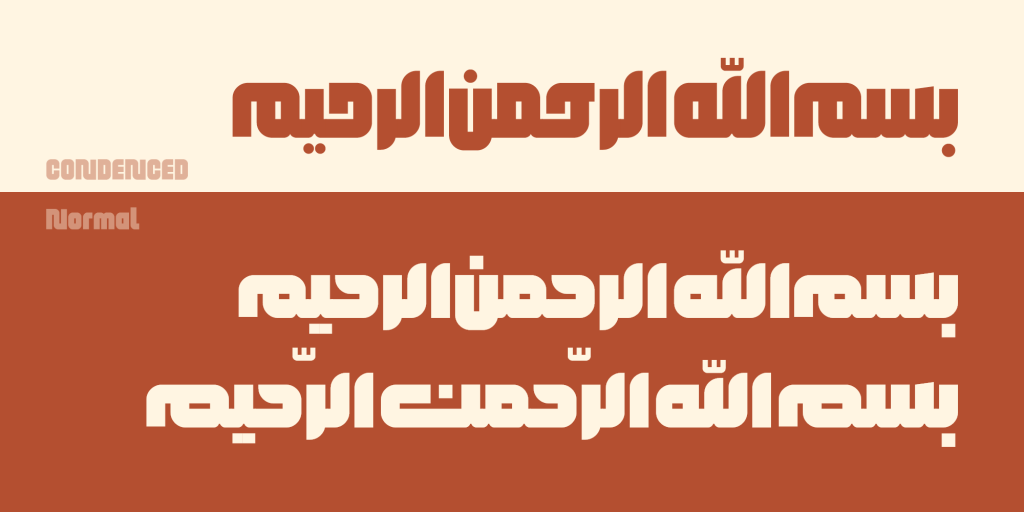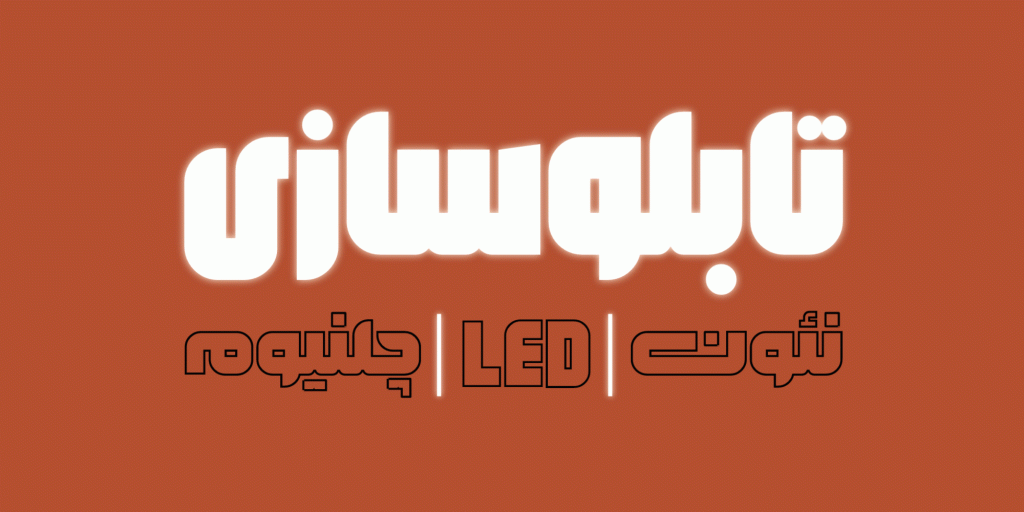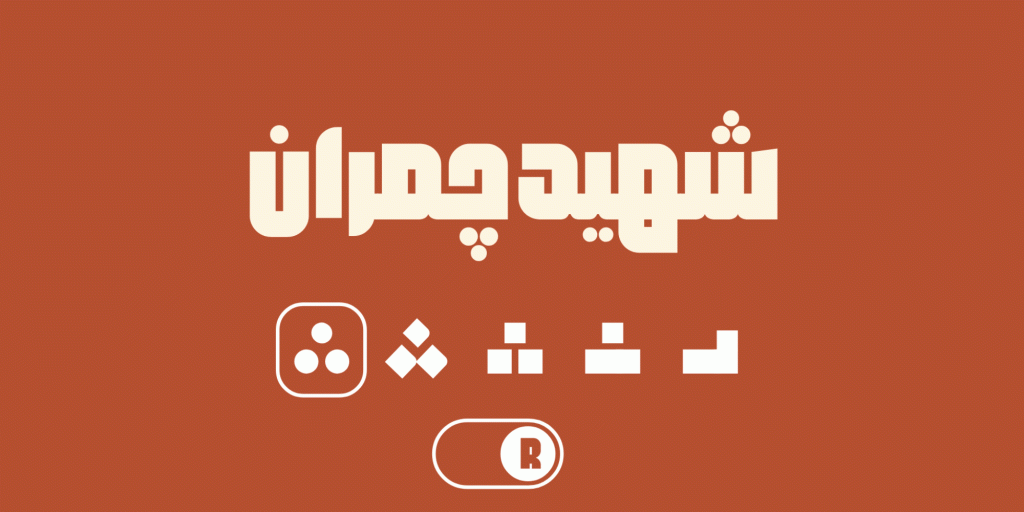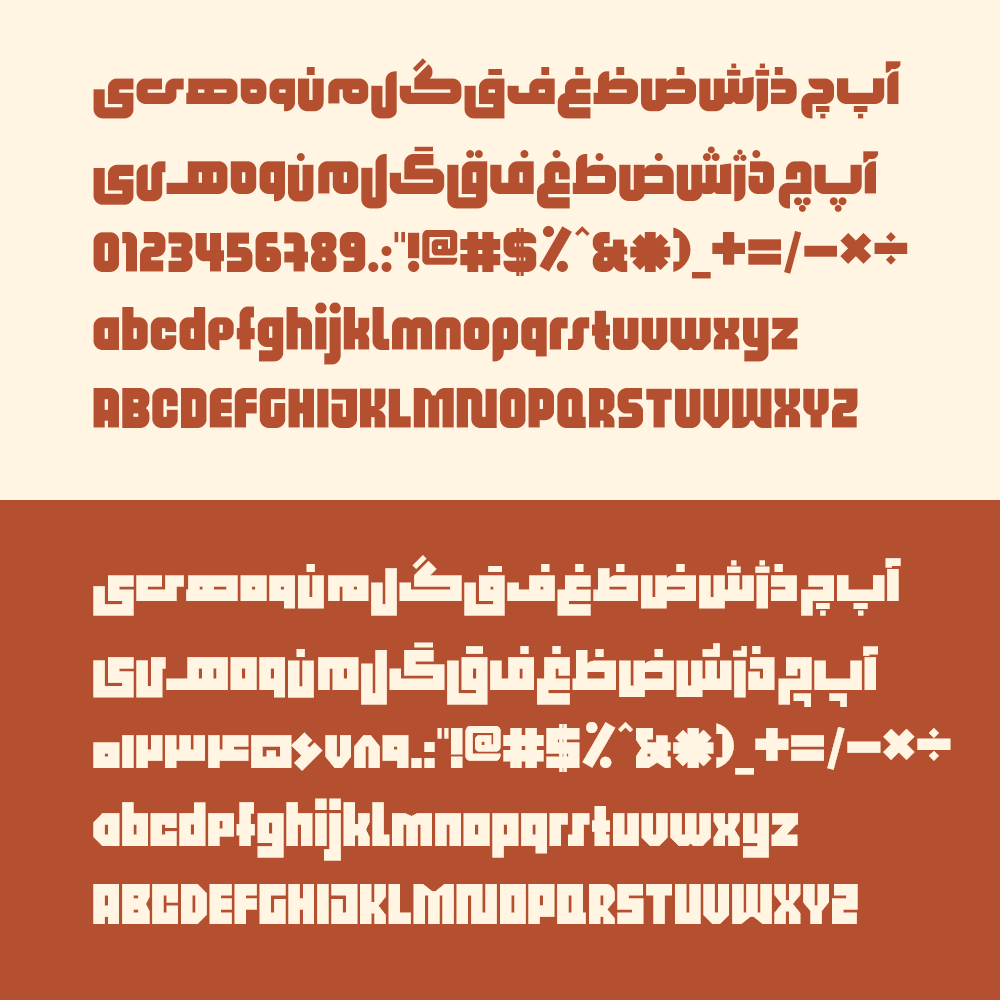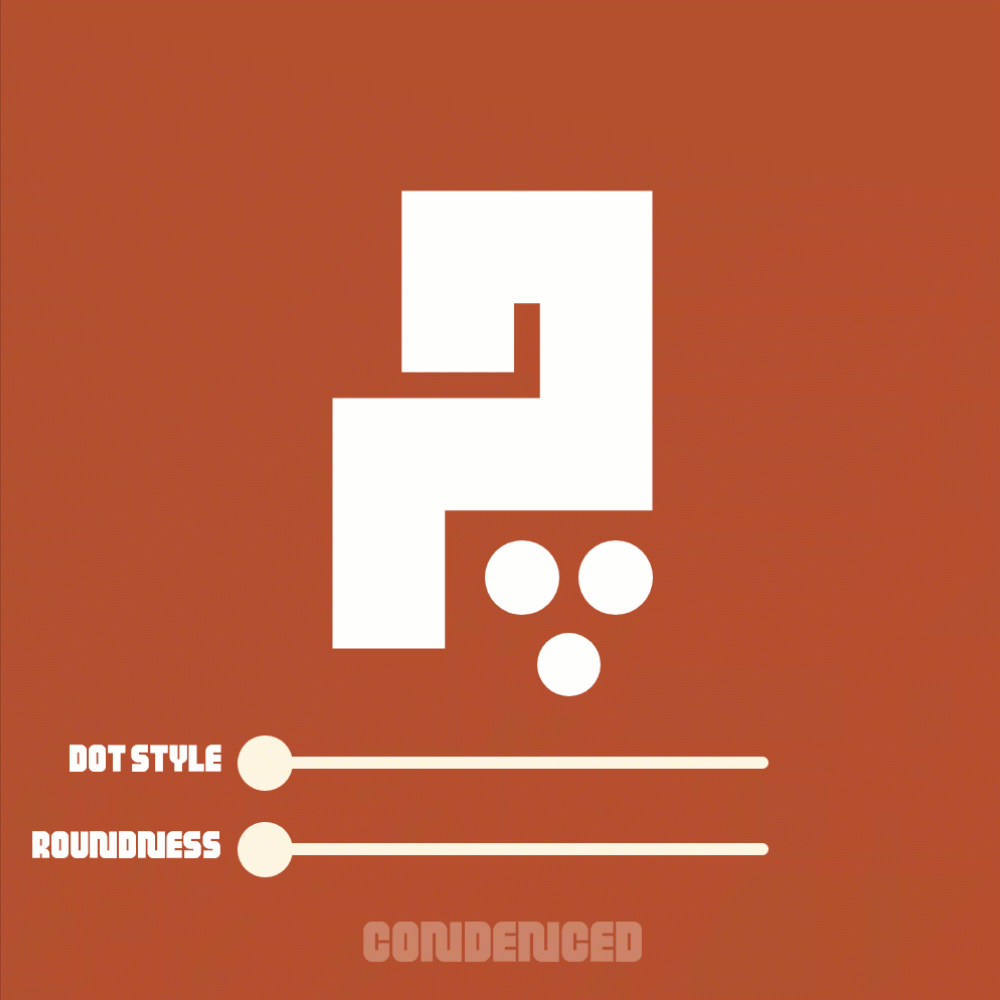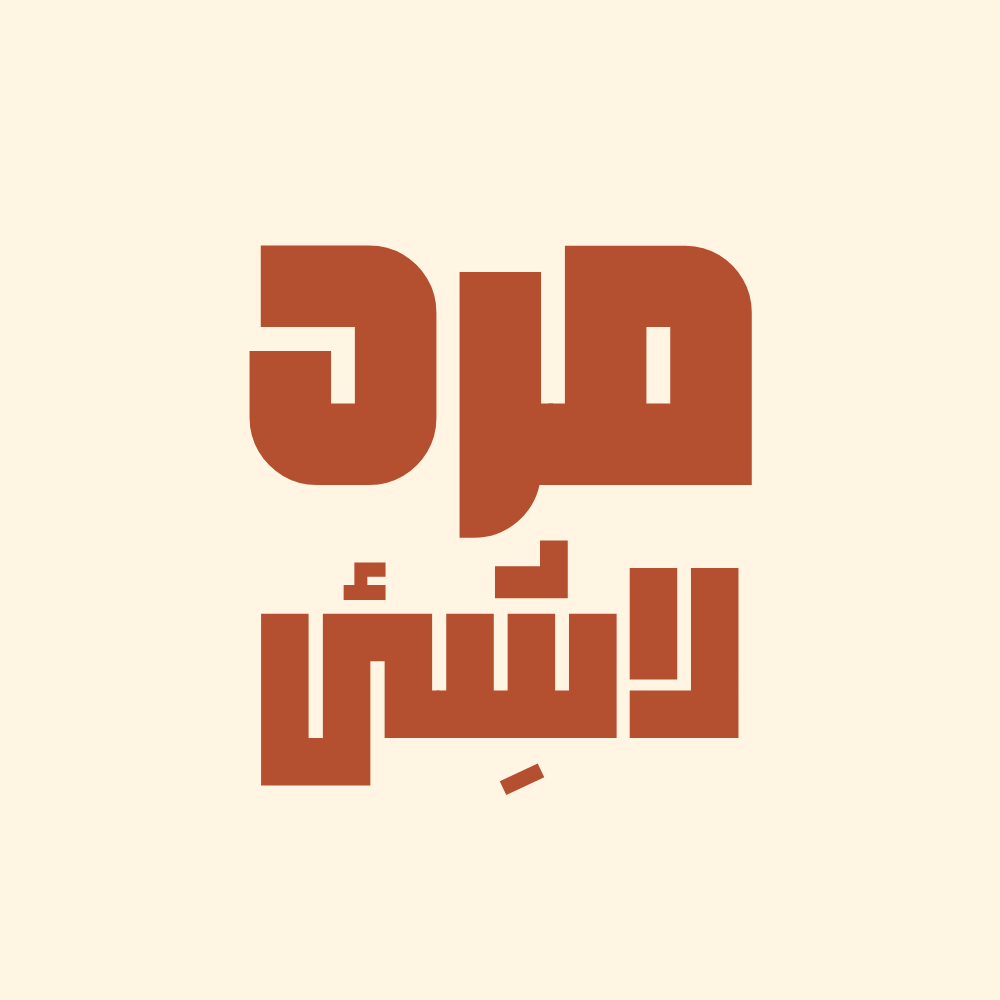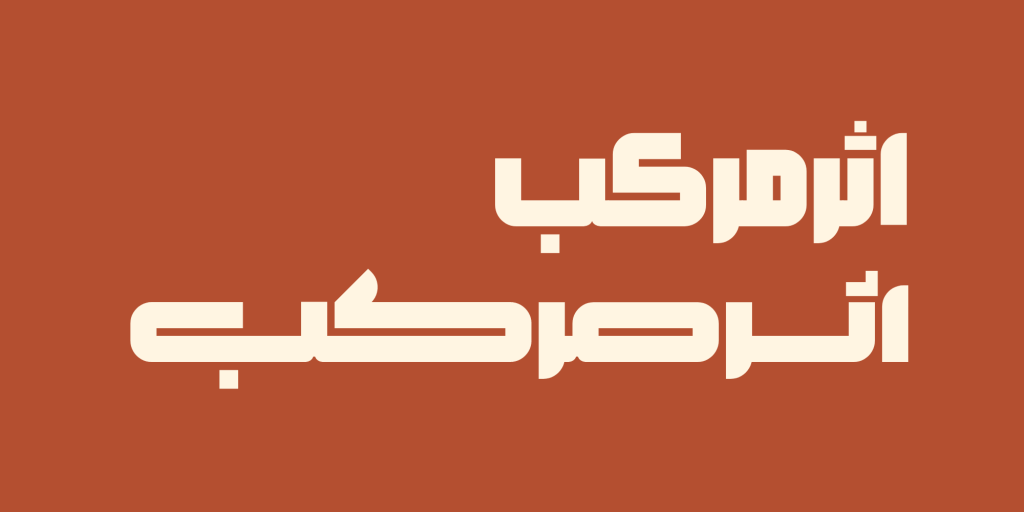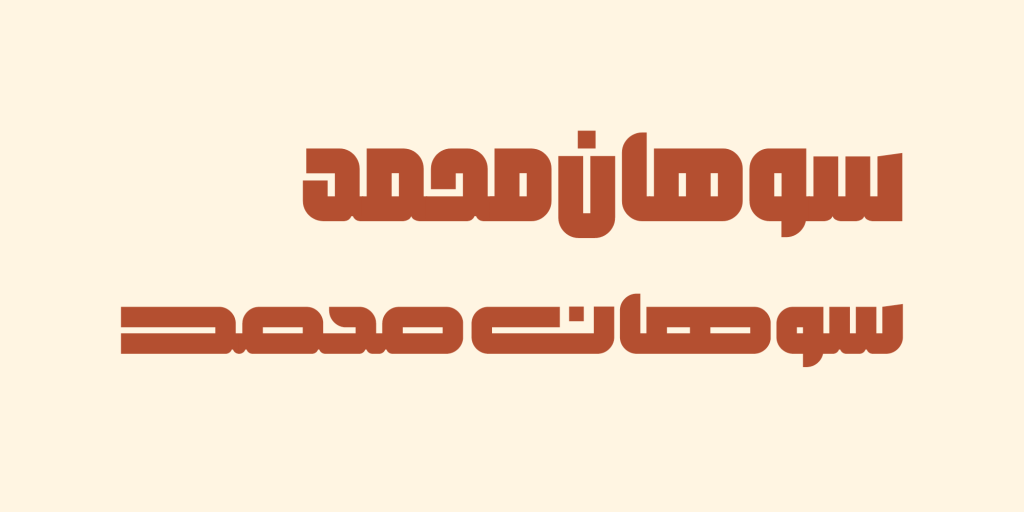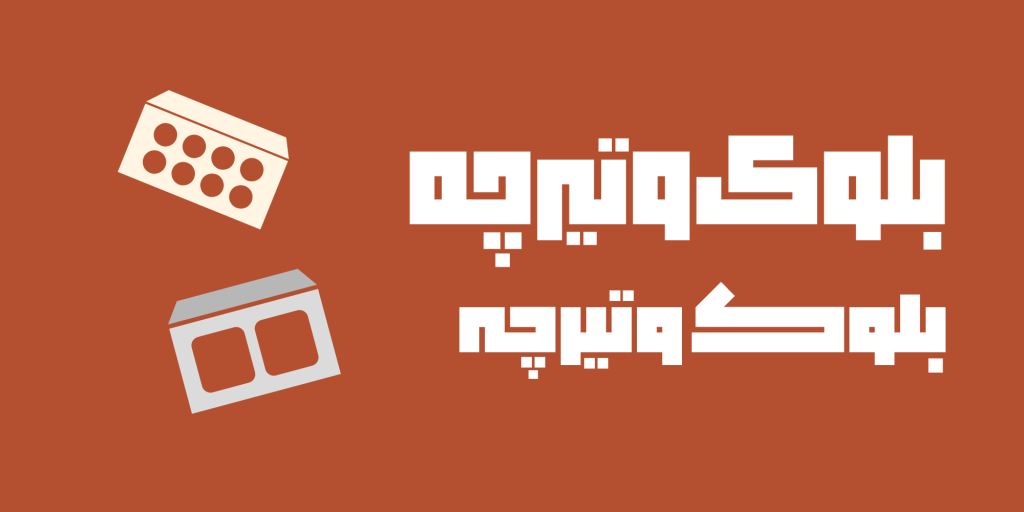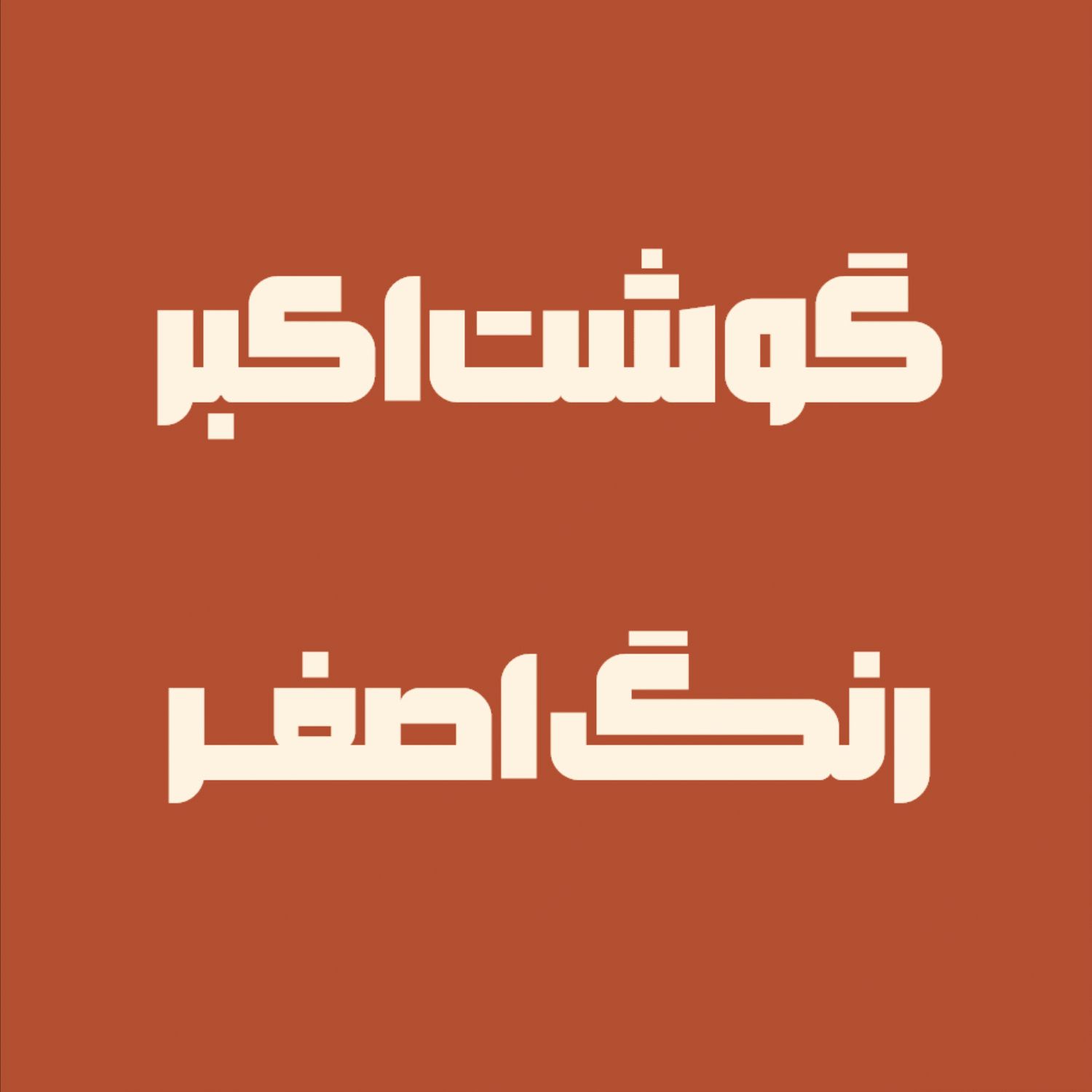
فونت بلوک – قلمی نمایشی
فونت بلوک با همکاری طراحان آقای عابدی و سعادت فر ایجاد و ابداع شده است. نام این قلم بیگانه از ماهیت و شاکله اصلی در طراحی آن نیست .چنانکه در طراحی حروف از بلوک های خط کوفی بنایی یا معقلی الهام و اقتباس شده است .
یعنی اجزای تشکیل دهنده حروف و گلیف های آن بلوک های مربعی و مستطیلی می باشد ، بلوک الهام گرفته و اقتباسی از خط بنایی یا معقلی می باشد که به دلیل ارتباط عمیقش با آجر و ساختمان ساختار مبتنی بر مربع و مستطیل دارد.
این تایپ فیس در دو استایل فرمی و شخصیتی ساخته شده است: یکی استایل سخت یا Sharp که دقیق، منظم، خشک است و آن دیگری استایل نرم یا Round که شخصیتی نسبتا مهربان، صمیمی و دوستانهتر دارد و به قول معروف سعی میکند با گفتگو مسئله را حل کند!
به سبب داشتن دو استایل متفاوت که هر کدام دنیای خود را دارند و با یکدیگر تفاوت محسوسی دارند بلوک دارای چندین شخصیت متفاونت و مجزایی می باشد و بهتر است متناسب با موضوع و محتوا از آنها استفاده بهره مند شوید. قلم هم خانواده و نزدیک به این تایپ فیس فونت دلنیا می باشد.
پشتیبانی بلوک از حروف جایگزین
به جهت ایجاد خلق زیبایی و تنوع بیشتر از قابلیتهای خط بنایی حداکثر استفاده گردیده و در نتیجه تعدادی مفردات و ترکیبات جایگزین به حروف اضافه شده که به کاربران امکان خلاقیت و نوآوری بیشتری را ارائه میدهد.
علاوه بر امکان بالا به ایتن تایپ فیس در راستای ساختار بنایی خود و بدون تغییر در فرم اصلی آن قابلیت انعطاف بیشتر و ایجاد کشیدگی های نوین به حروف آن افزوده گردیده است. می توانید در تصاویر نمونه از این تایپ فیس حروف جایگزین مذکور را مشاهده کنید.
در بستهی حرفهای این محصول میزان نرمی گوشه ها و نقطهها و همچنین استایل نقطهها و فضای خالی چشم حروف با محورهای متغیر در دامنهی گستردهای قابل تغییر است.
بخشی از توضیحات طراح را در باره نحوه و مسیر ایجاد و شکل گیری برای شما عزیزان نقل قول می کنیم “یکی از موضوعاتی که در بروزرسانی این قلم و بافراگیری مطالب جدیدی در کلاس استاد خانجانزاده و دوست عزیزم رضا مرادی سعی در اعمال و اجرای آن داشتم اصلاحات اوپتیکال بود که تا حد امکان از دچار شدن مخاطب به خطا یا توهم بصری یا Optical Illusion جلوگیری کند، اگرچه این موضوع کمتر درمورد فونتی مثل بلوک ممکن است رخ بدهد اما موارد محدودی بودند که با بررسی و اصلاح آنها تاثیرات زیادی را در تناسبات و خوانایی مشاهده کردم.”